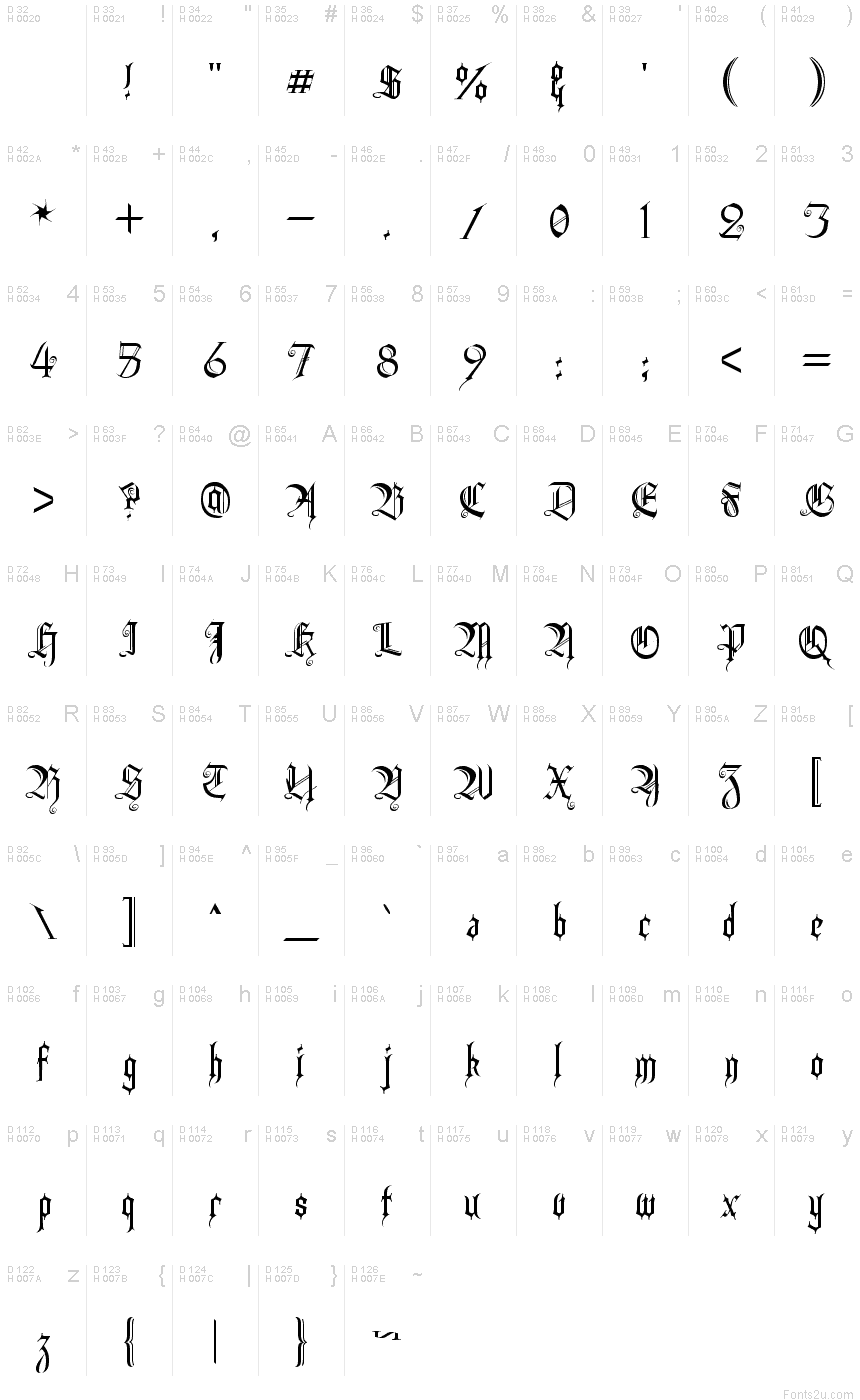
Heidorn Hill autorstwa Grahama Meade'a to darmowy średniowieczny krój gotycki. Jego wysokie, przypominające ostrza linie i zahaczone krzywizny wyglądają, jakby zostały wyryte w kamieniu, a gęste plamy tuszu i kolczaste zdobienia natychmiast przywodzą na myśl mroczne fantasy i magię starego świata. Rytm pisma jest zwarty i dramatyczny, dzięki czemu nawet krótkie słowo wygląda bardziej jak herb lub pieczęć niż zwykły tekst.
Dzięki Heidorn Hill nagłówki i logotypy nabierają ceremonialnego, niemal rytualnego klimatu, który świetnie sprawdza się w identyfikacjach zespołów metalowych, okładkach książek fantasy, tytułach gier RPG, plakatach wydarzeń, projektach tatuaży czy grafice odzieżowej. Ten darmowy font najlepiej prezentuje się w dużych rozmiarach, pozwalając wybrzmieć misternym kolcom i zamaszystym wielkim literom. Jako tekst uzupełniający warto dobrać czysty geometryczny krój bezszeryfowy, aby zachować czytelność, podczas gdy Heidorn Hill zajmie się budowaniem atmosfery.